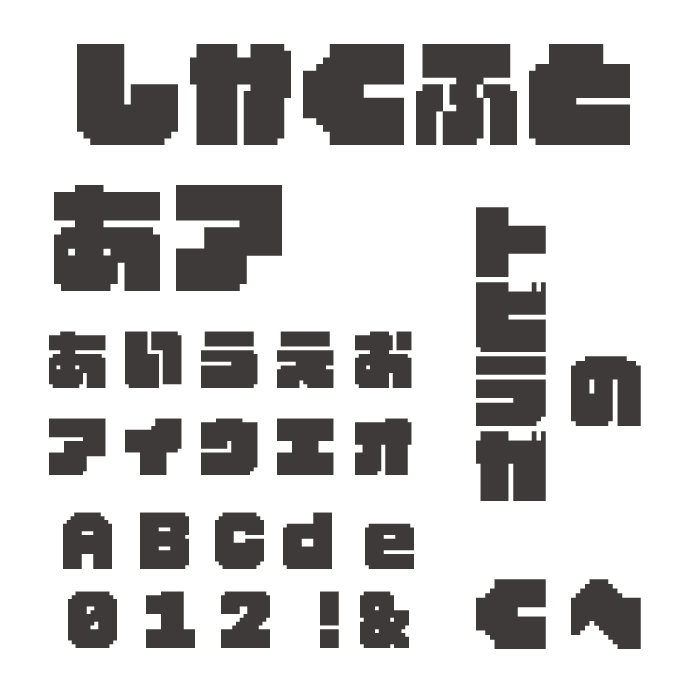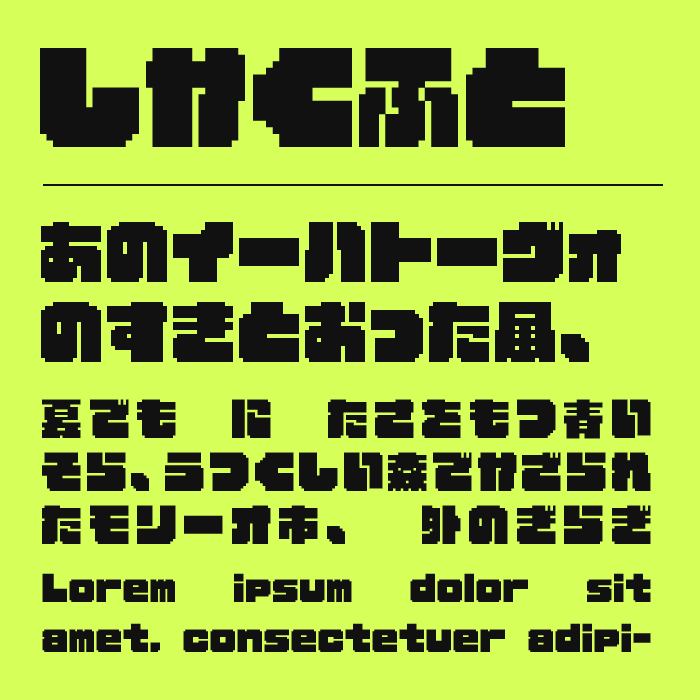
しかくふとフォントは、太めのドットで構成された無骨なシルエットが特徴的な極太なピクセルフォントです。
角ばった形状をベースにしながらも、完全に均一ではない輪郭によって、どこかレトロゲーム機のタイトル画面を思わせる独特の空気感があります。力強く詰まった字面が印象的で、短い単語でもしっかりと視線を引き寄せてくれるフォントです。
ゲーム風デザインやデジタル系ビジュアル、動画サムネイルなどと相性が良く、画面全体に懐かしくもエネルギッシュな雰囲気を加えられます。
シンプルながら存在感があり、レトロポップな世界観を楽しく演出できるフォントです。
収録文字は、漢字(無料版は小学2年生までの漢字)・ひらがな・カタカナ・アルファベット・数字・記号が収録。